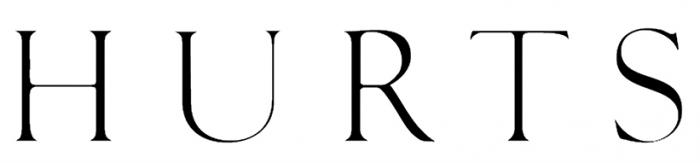
Woher stammt das?
Diese runden Übergänge (z. B. beim Querstrich des H) lassen mich ja vermuten, dass da irgendeine Art Weichzeichnung mit anschließender automatischer Nachzeichnung oder Ähnliches verwendet wurde.
Sehe ich auch so. Ein Schriftgestalter würde nicht solche komischen inkonsistenten Serifen bauen. Als Artefakt einer künstlichen Bearbeitung ist das aber gut denkbar.
Deren Homepage verwendet die Trajan Pro … nur so als Hinweis.
Ich habe es mit der Trajan mal schnell ausprobiert.Ich  habe zwar nicht 100%ig die Einstellungen getroffen, aber im Prinzip sieht es schon so aus...
:tuschel: Nur so als Anmerkung, catfonts (um Unhitzen nicht auf die falsche Fährte zu locken): ich würde behaupten wollen, dass die Trajan dennoch nicht als Grundlage für die Wortmarke diente, weil zum Beispiel das S und U dort breiter sind. Den »Blur-Zauber« hatte ich aber auch vermutet.
Auch möglich.Mit einem Grafikprogramm hat man ja unendlich Möglichkeiten eine gute Schrift zu vermurksen. Und manchmal (?) wird das dann auch noch als toller neuer Font angeboten.
Stimmt, Robert, das wird eine Outline sein – dabei bleiben dann auch die spitzen Winkel erhalten, was bei der Blur-Geschichte nicht der Fall ist.